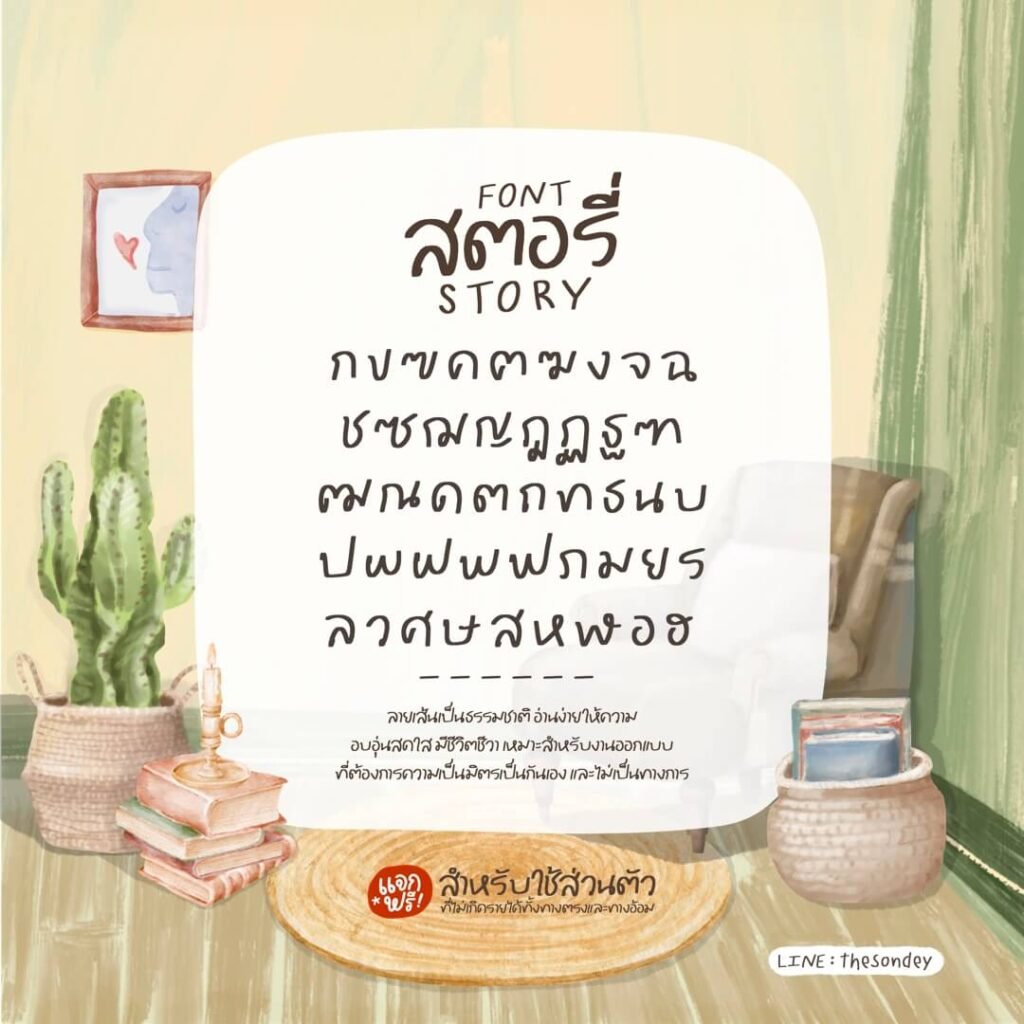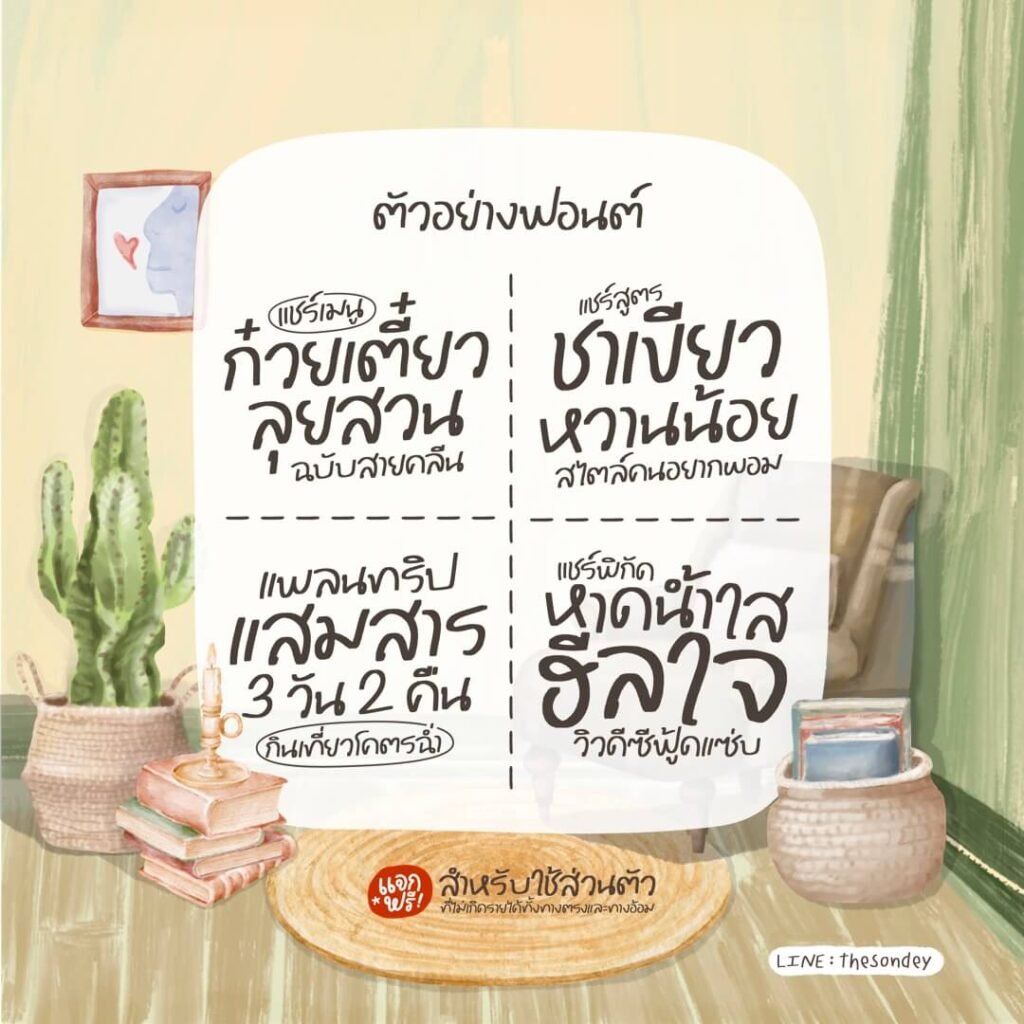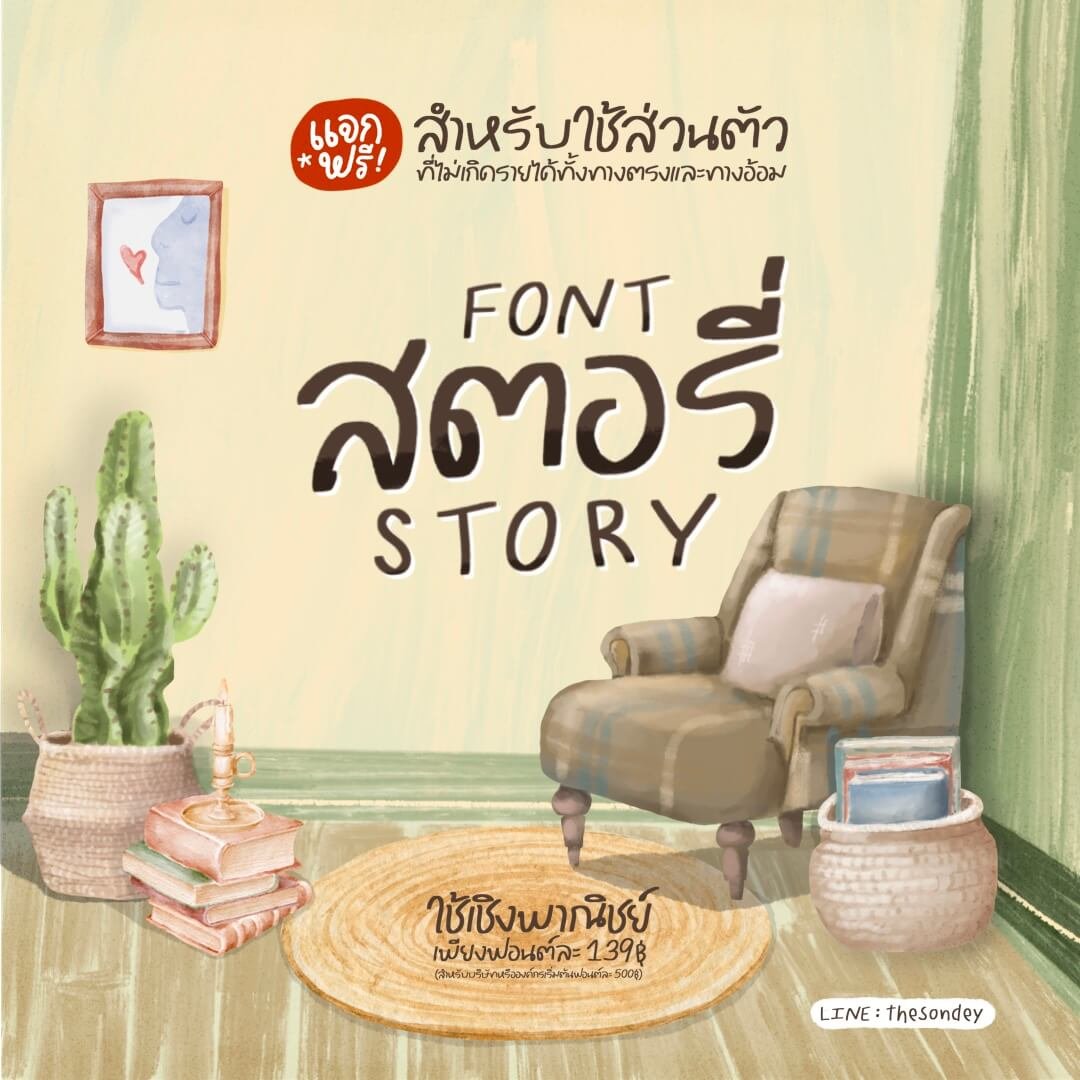
สตอรี่ (PG Story)
ฟอนต์ลายมือสไตล์น่ารักปุ๊กปิ๊ก อ่านง่าย รองรับ Microsoft, Photoshop, Illustrator, CapCut, ibisPaint, Procreate, Good Note และแอปฯ ต่างๆ ที่มีให้ติดตั้งฟอนต์